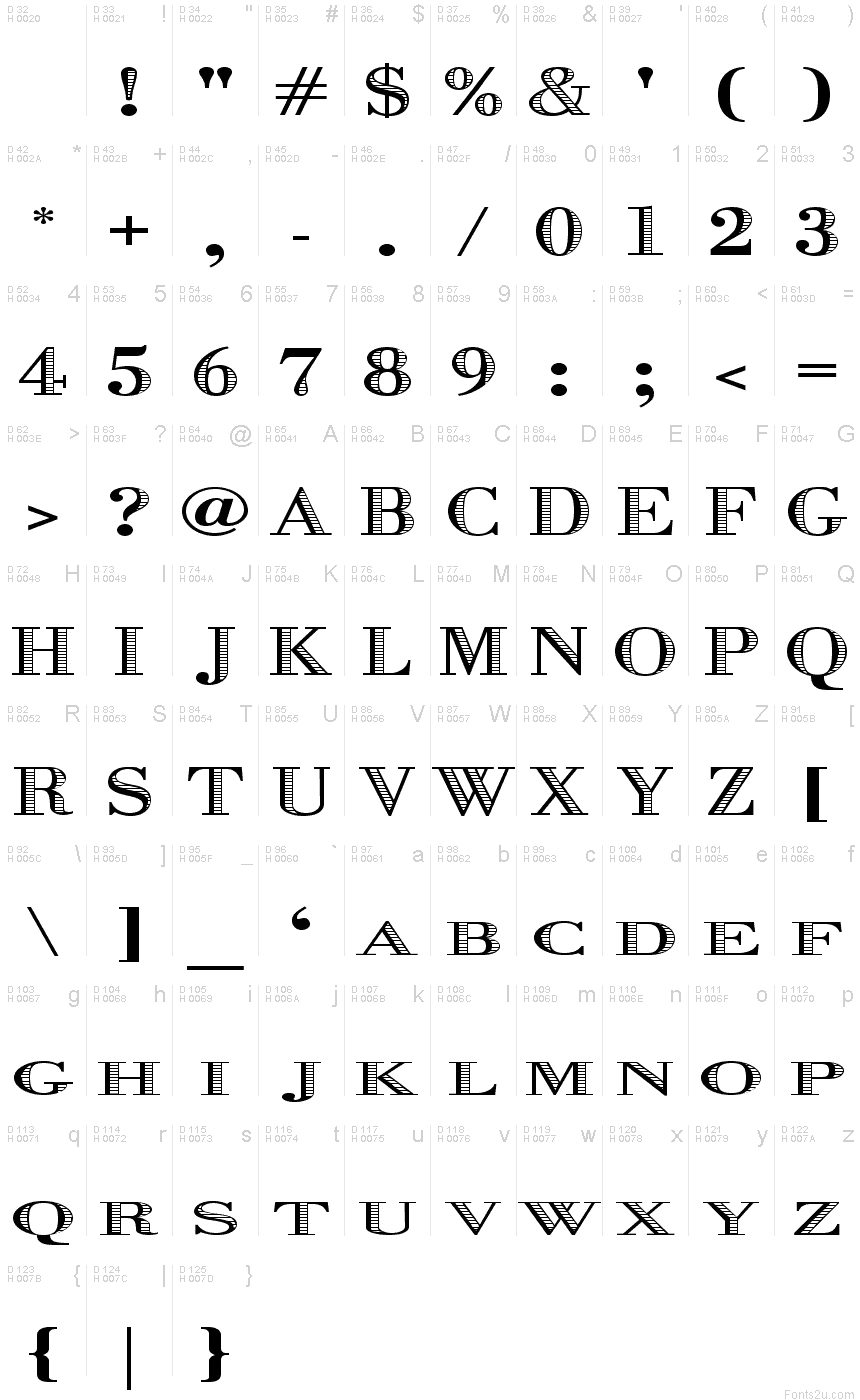
Graphis to darmowy, dekoracyjny krój szeryfowy w stylu retro z odważnym, teatralnym sznytem. Szerokie, wyraziste litery wypełnione gęstym poziomym prążkowaniem przywodzą na myśl stare kinowe afisze lub bilety sprzed lat, nadając każdemu słowu teksturowany, głęboki charakter. Mocne zewnętrzne kontury zapewniają czytelność, a prążkowane wnętrza dodają dynamiki i rytmu, które sprawiają wrażenie niemal ręcznie malowanych.
Graphis sprawia, że nagłówki zyskują natychmiast nostalgię i show-biznesową energię, idealną na plakaty, okładki książek, opakowania retro, ulotki wydarzeń, szyldy czy wyraziste logotypy. Ten darmowy font najlepiej prezentuje się w dużych rozmiarach, gdzie wewnętrzne prążki mogą w pełni wybrzmieć. W przypadku tekstu pomocniczego warto zestawić Graphis z prostym krojem bezszeryfowym, aby jego styl retro mógł w pełni zaistnieć.
Graphis